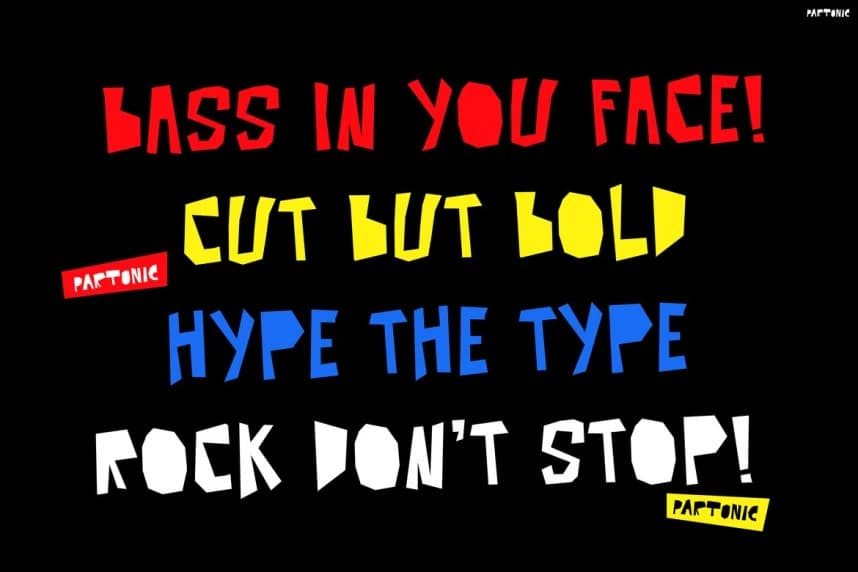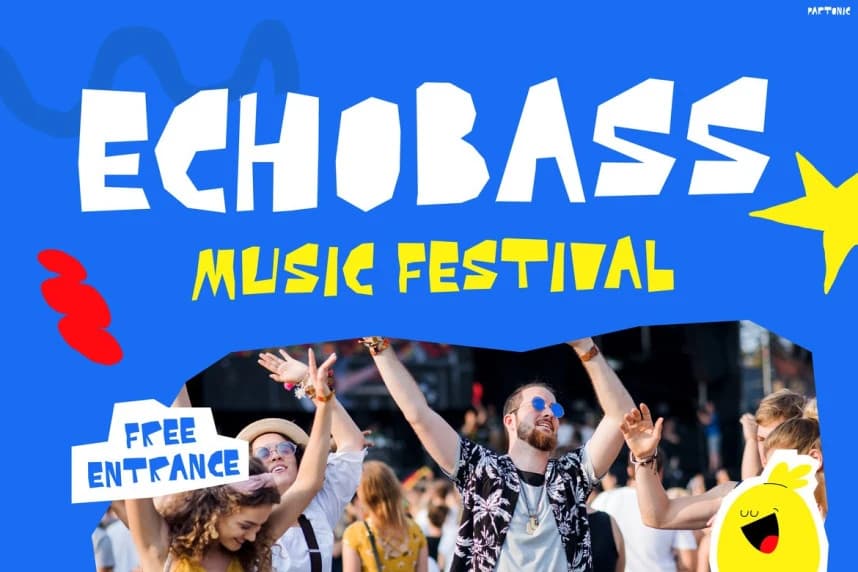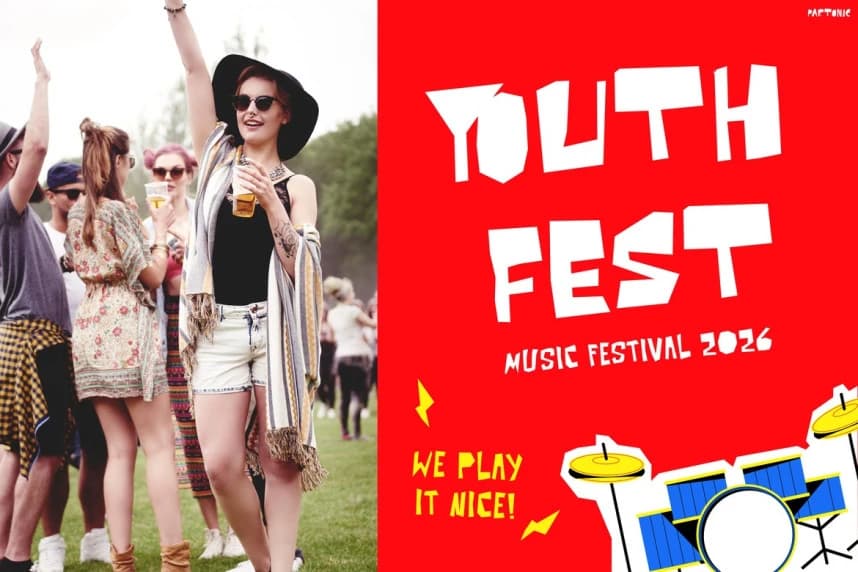
Partonic Display Font
Partonic Display Font, cesur ve yüksek enerjili bir müzik fontudur ve keskin, çarpıcı harf biçimleriyle herhangi bir tasarımı anında güçlendirir. Keskin, düzensiz şekilleri canlı konserlerin ve yeraltı müzik sahnelerinin ham yoğunluğunu yansıtır.